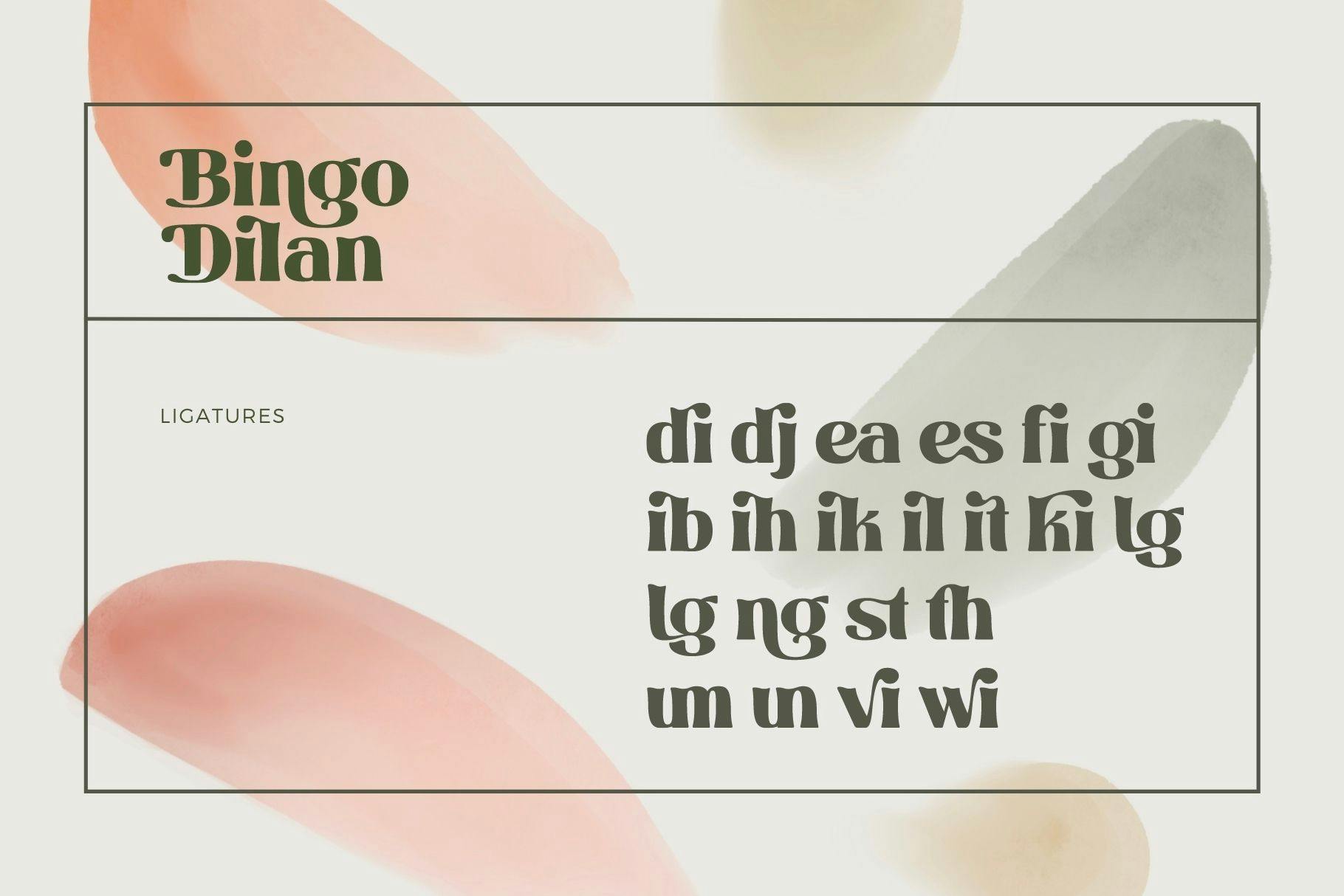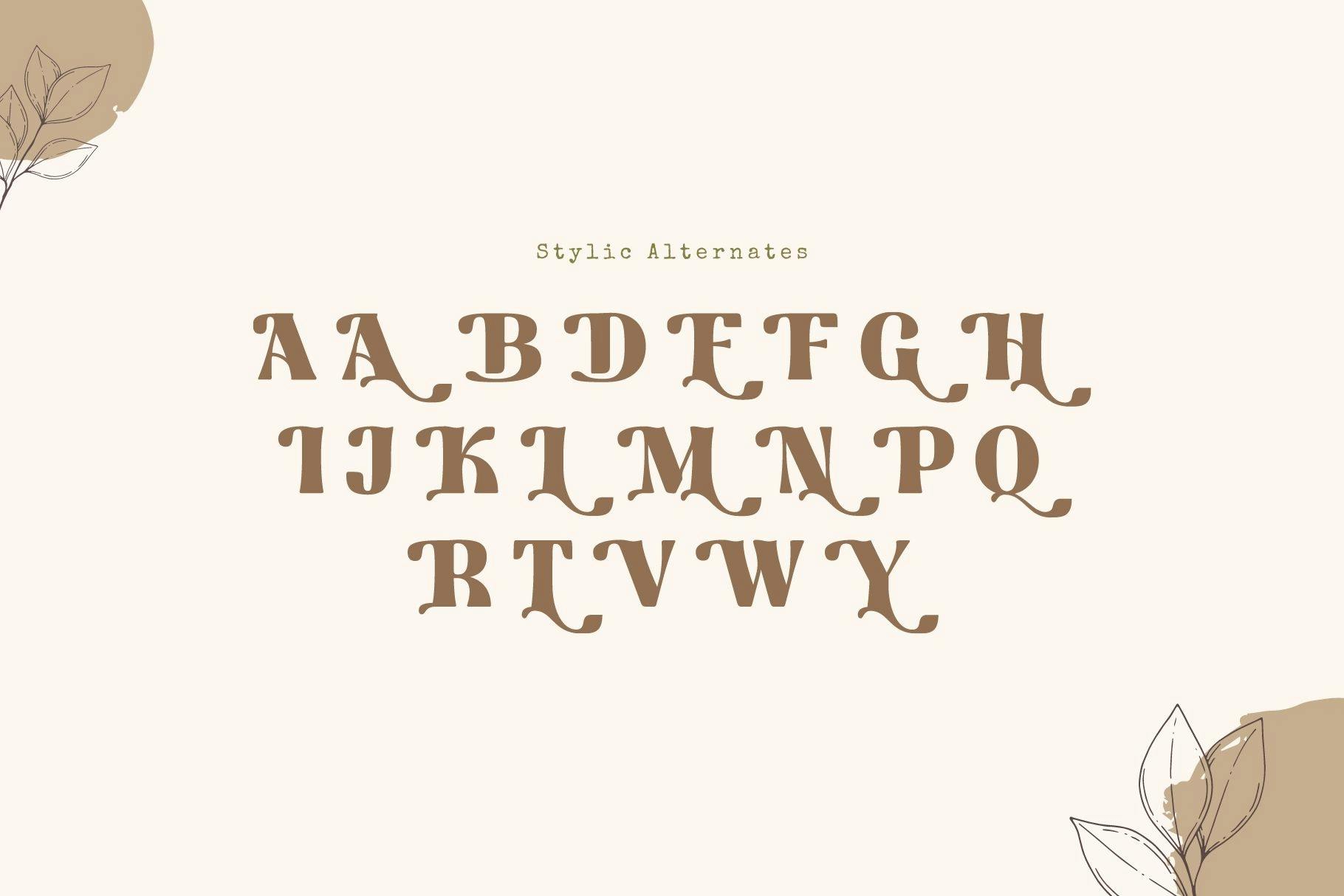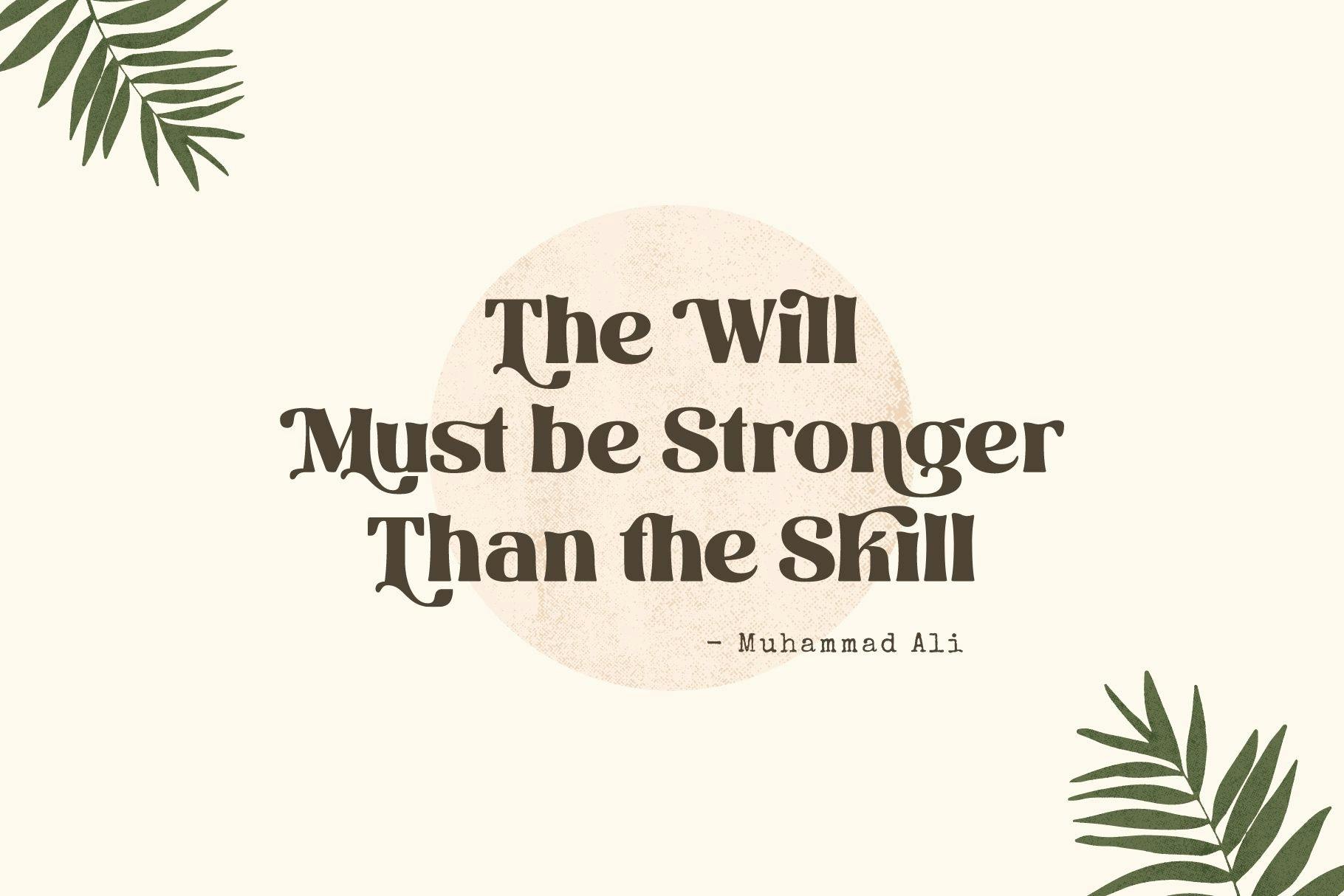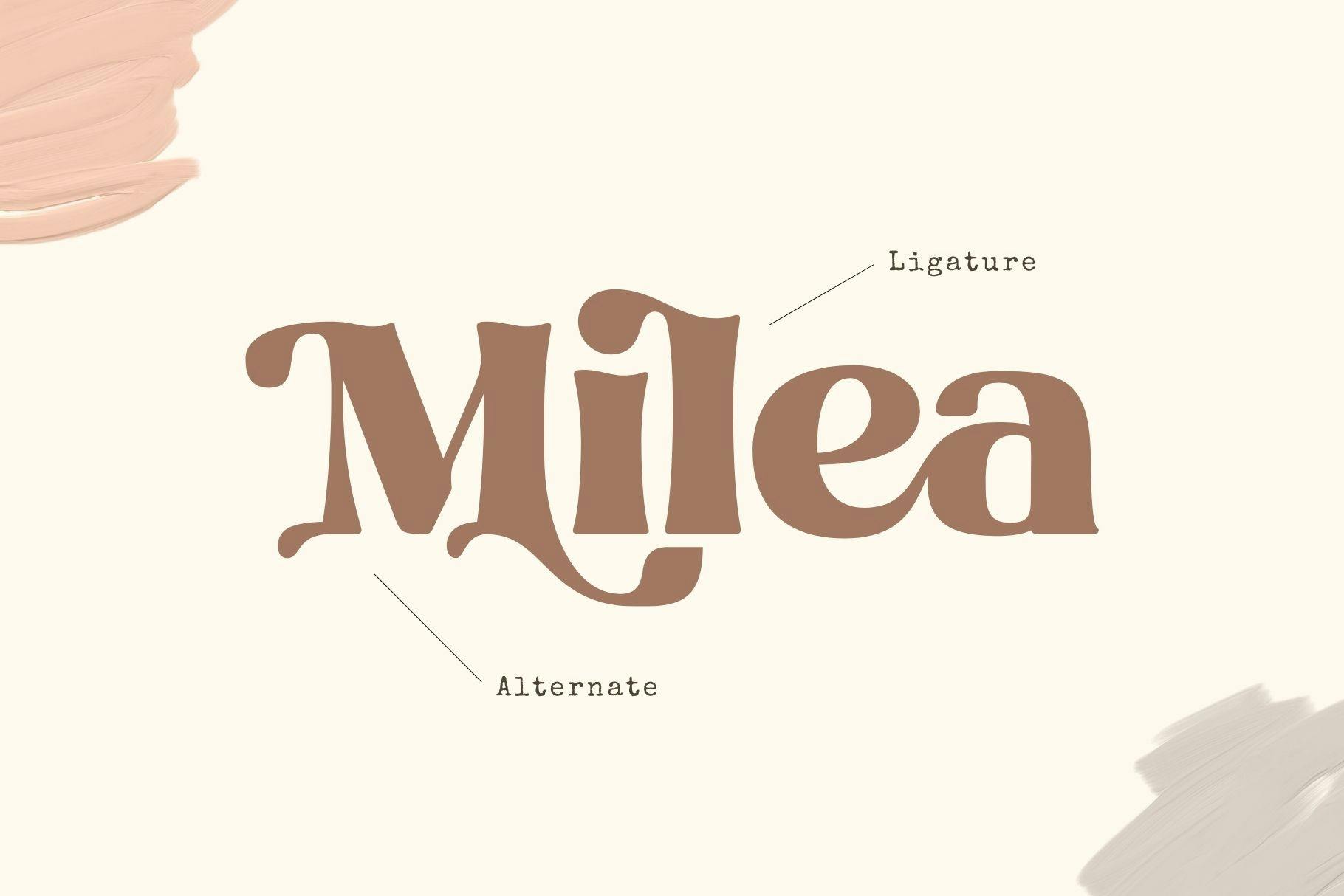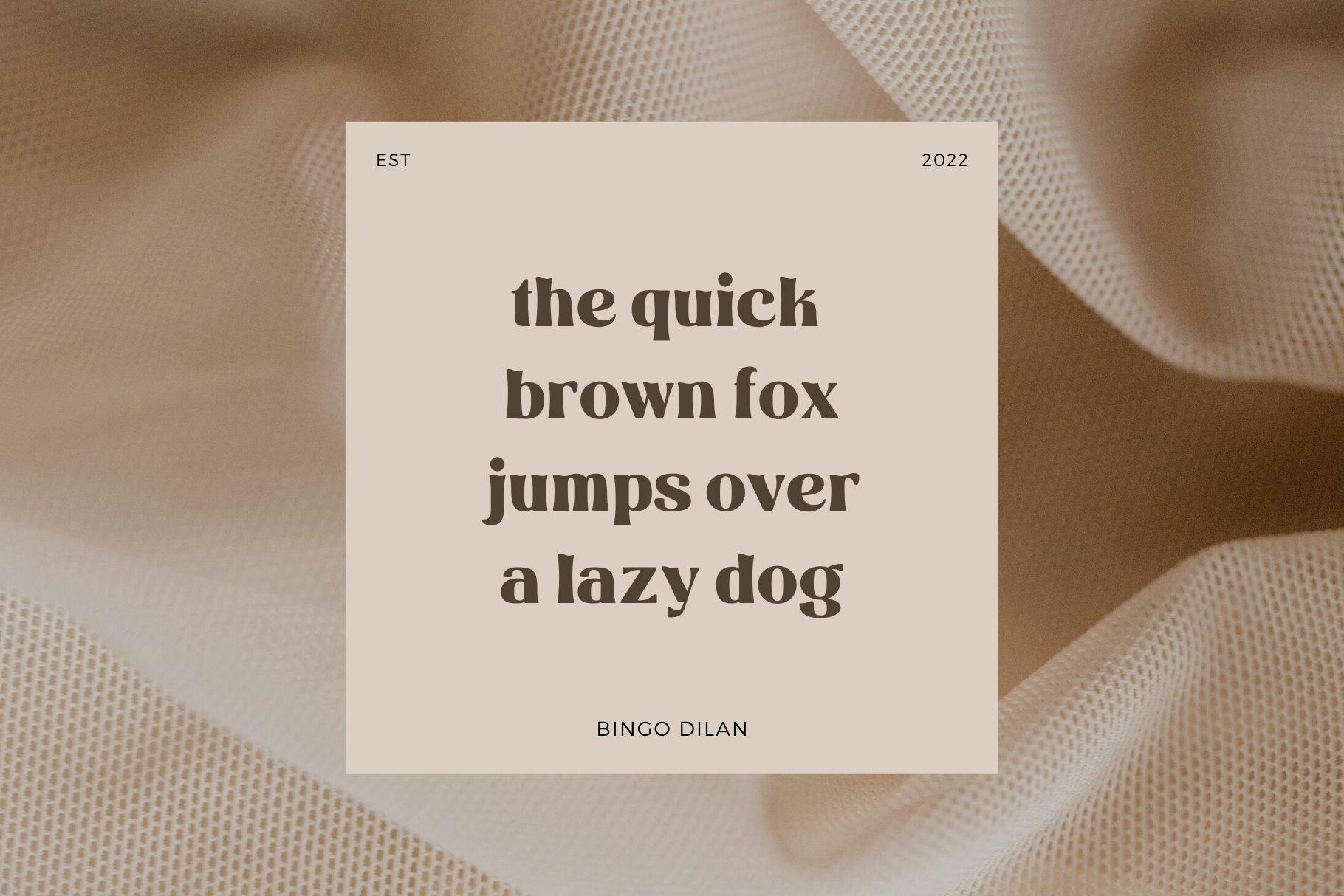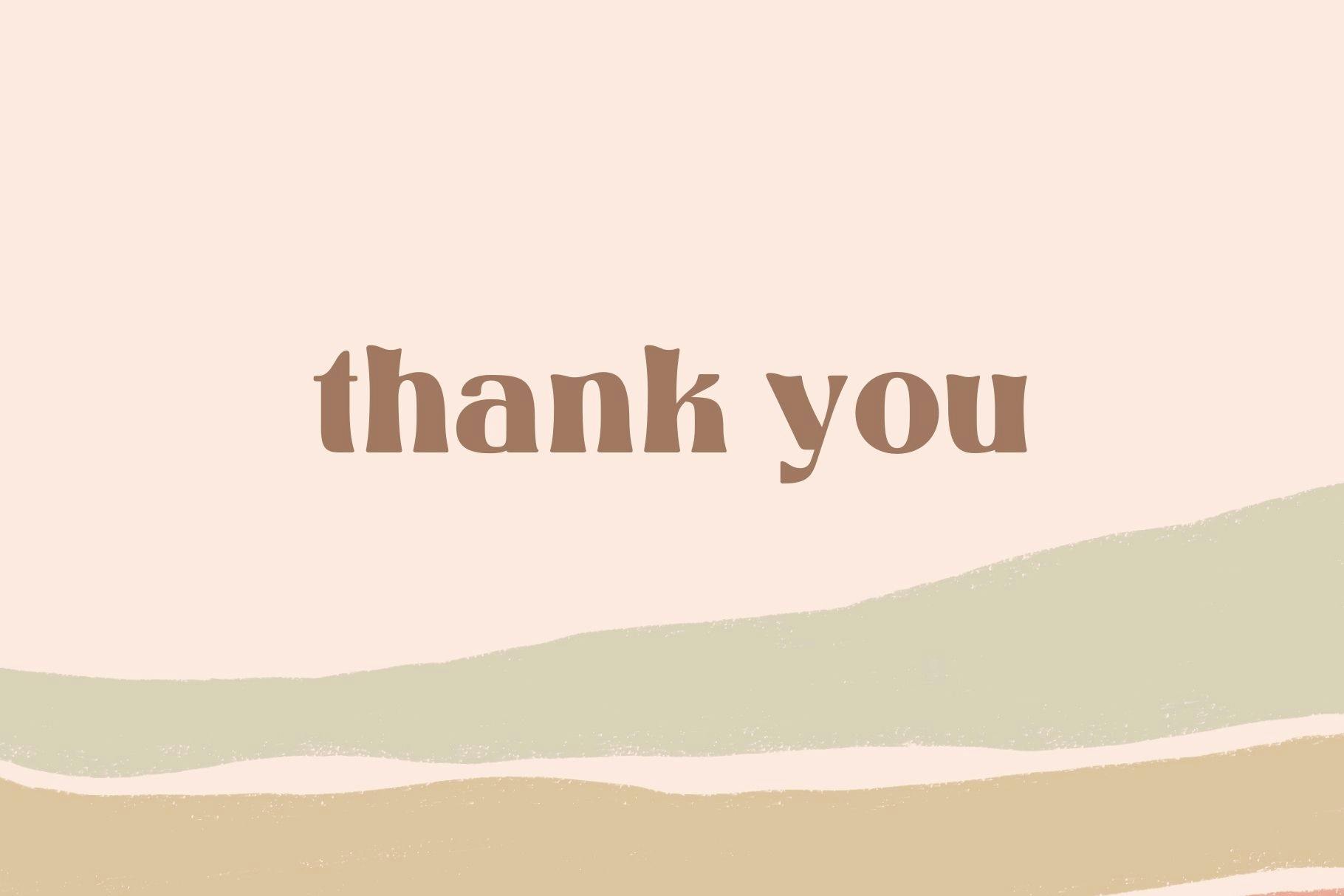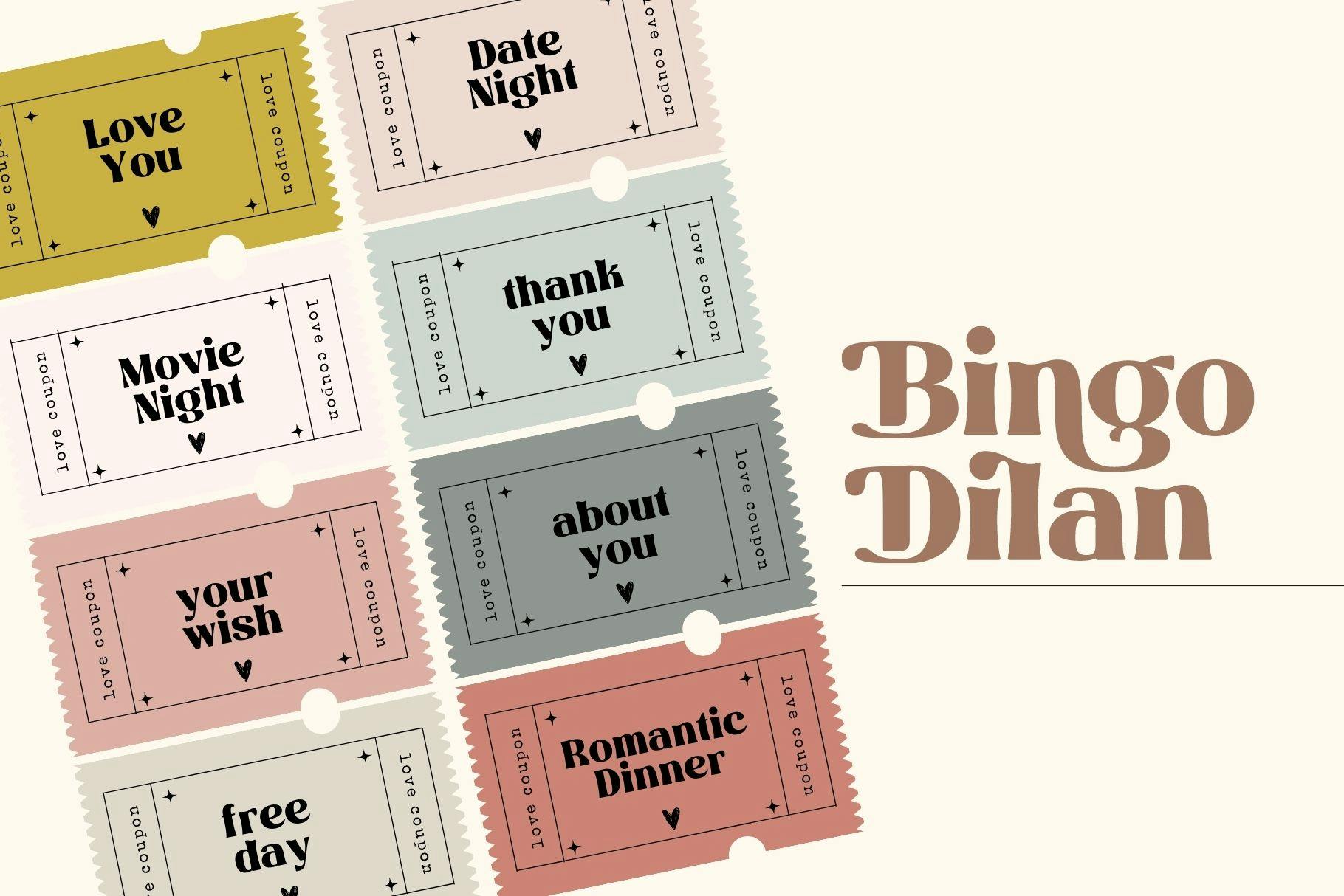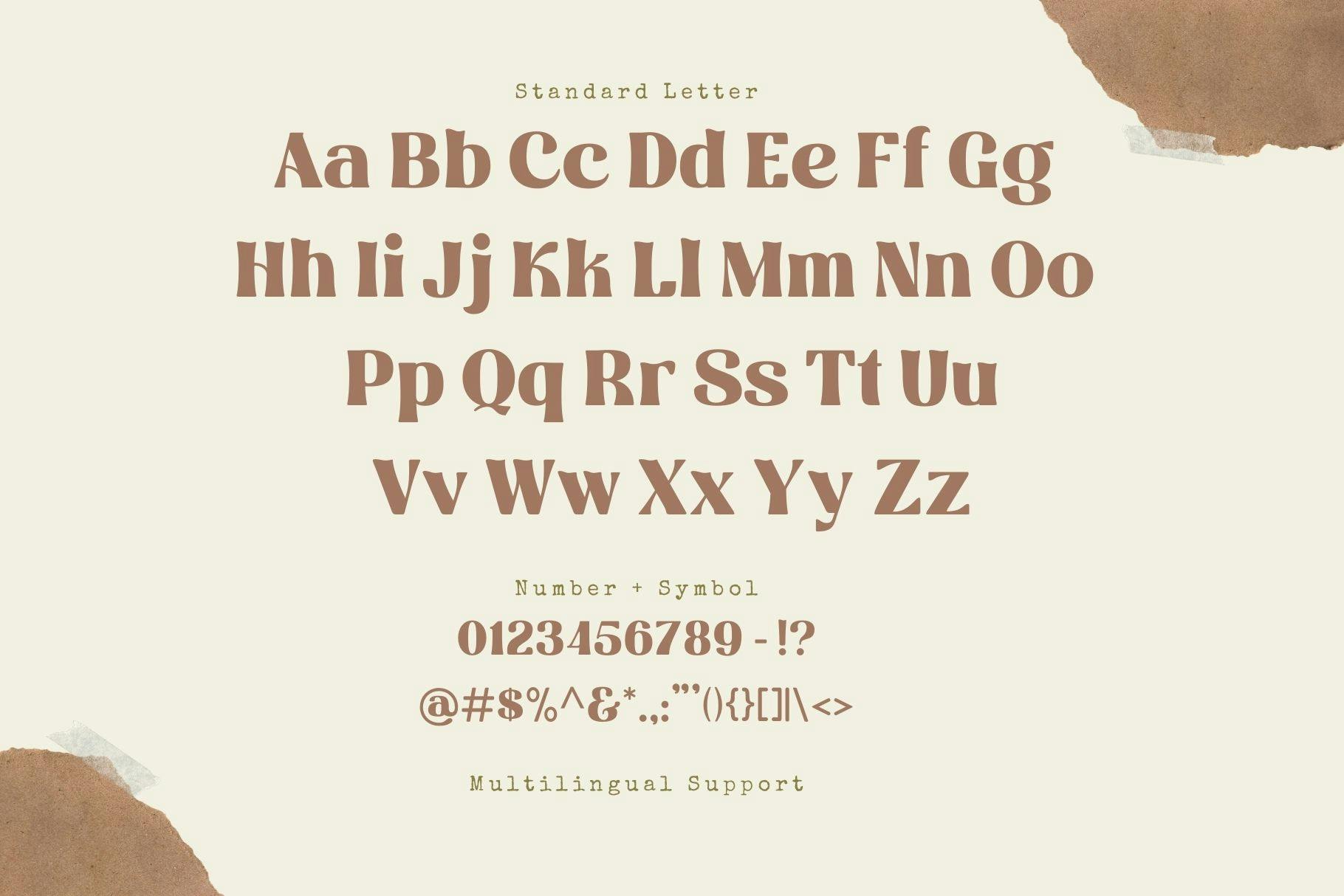
Bingo Dilan یک فونت مدرن از نوع Serif است که هم به یاد ماندنی و هم شیک میباشد. این فونت ترکیبی از یک Serif کلاسیک و یک Sans Serif آیندهنگر است.
این فونت برای برندینگهای مرتبط با مد یا طراحیهای ویرایشی بسیار مناسب است و هم ویژگیهای مردانه و هم زنانه را به نمایش میگذارد.